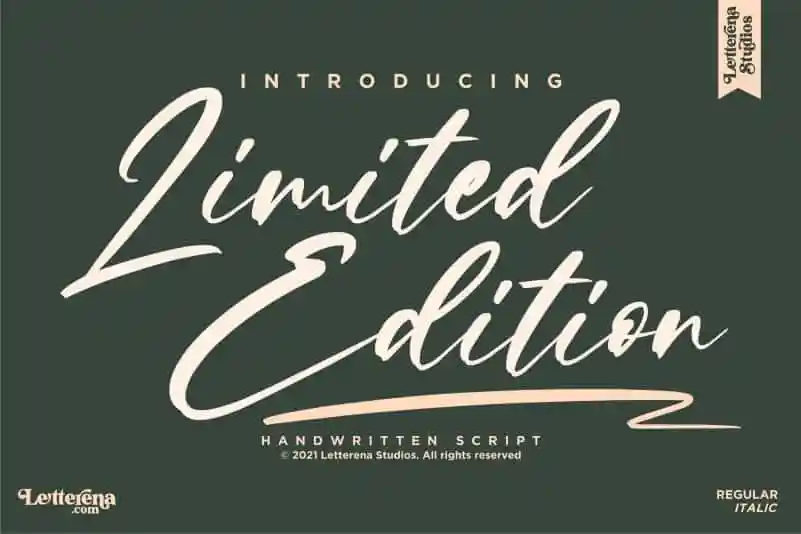
Limited Edition Script Font – Download Grátis
A Limited Edition Script Font é uma fonte elegante projetada pela Letterena para aqueles que desejam adicionar um toque especial às suas criações. Essa fonte tem uma influência romântica da caligrafia, perfeita para aplicação em diversos tipos de projeto. Suas linhas fluidas e delicadas são ideais para aplicações como logotipos, identidade visual, designs de objetos caseiros, embalagens de produtos, pratos, cartazes, sacolas de presente, camisetas, capas de livros, cards de nome, convites, cartões de agradecimento e etiquetas. A Limited Edition Script Font também é perfeita para adicionar um toque único em materiais como papelaria, fotografia, marca d’água e eventos especiais. Com sua arquitetura sofisticada, ela tornará suas criações ainda mais impecáveis e de luxo. Seja você um designer gráfico ou uma pessoa que busca imprimir memórias no formato físico de forma elegante, a Limited Edition Script Font é o acessório perfeito para seu armário de fontes.